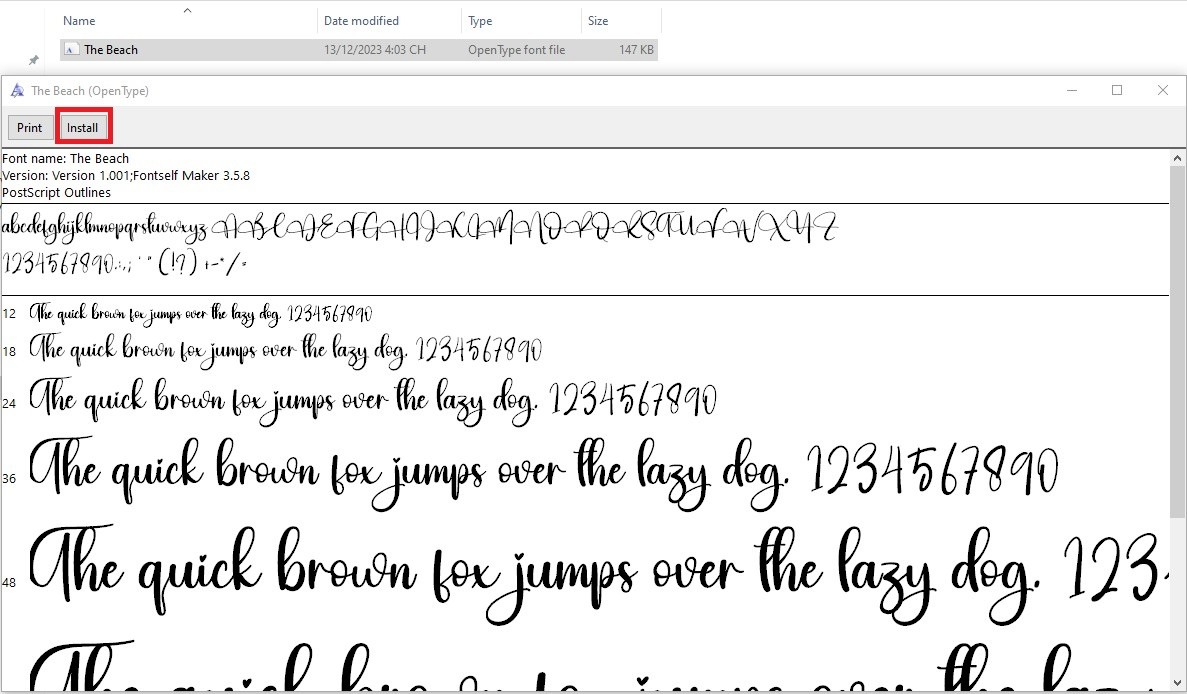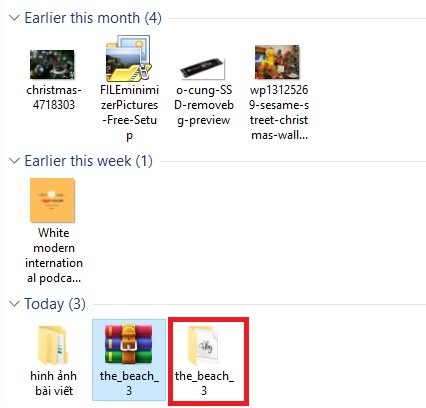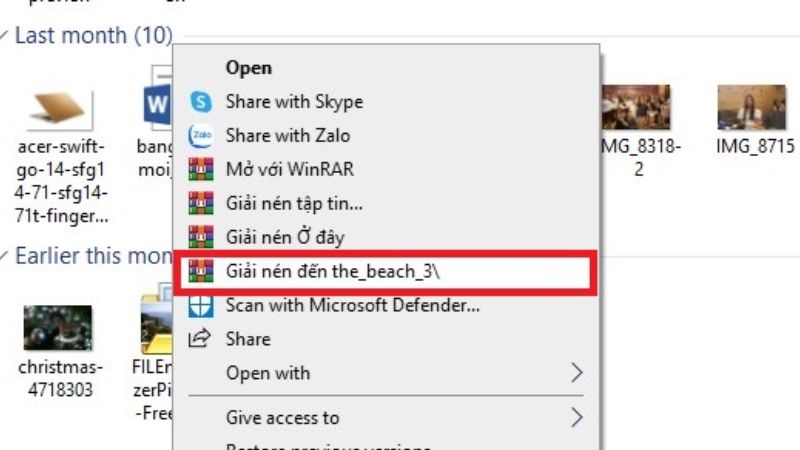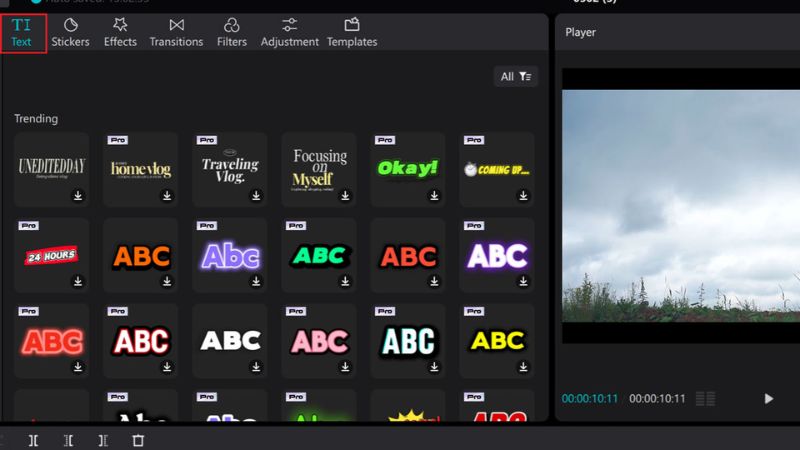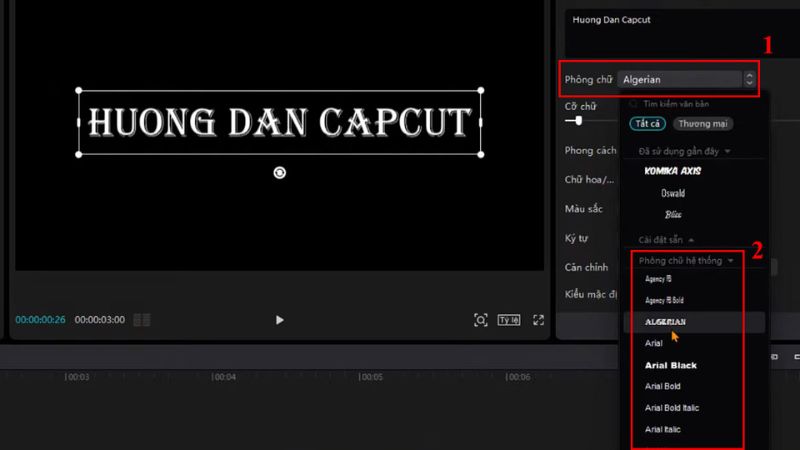
Thêm font chữ vào CapCut là một trong những giải pháp được nhiều người dùng lựa chọn khi muốn tạo ra những video chuyên nghiệp và mang đậm dấu ấn cá nhân,…. Tuy nhiên, không phải ai cũng biết cách thêm font chữ vào CapCut trên máy tính. Vì thế bài viết này của Điện Thoại Giá Kho sẽ hướng dẫn bạn cách thêm font chữ vào CapCut PC nhanh chóng và đơn giản nhất năm 2025.
Lợi ích khi thêm các font chữ vào CapCut PC
Việc thêm font chữ vào CapCut PC không chỉ đơn thuần là một bước tùy chỉnh giao diện văn bản, mà cách làm này còn mang lại nhiều lợi ích thiết thực cho những ai làm sáng tạo nội dung, đặc biệt là trong lĩnh vực video marketing, vlog, giáo dục hay giải trí. Dưới đây là những lợi ích nổi bật mà người dùng sẽ nhận được khi cài đặt font chữ tùy chọn vào CapCut PC:
Tăng tính thẩm mỹ cho video
Font chữ ảnh hưởng trực tiếp đến cảm nhận thị giác của người xem. Một font chữ phù hợp sẽ giúp phần tiêu đề nổi bật hơn, nội dung phụ dễ theo dõi hơn và tổng thể video trở nên chuyên nghiệp, cuốn hút hơn.
Đặc biệt, khi bạn kết hợp font chữ với hiệu ứng chuyển động, màu sắc và bố cục hợp lý, chất lượng video sẽ được nâng tầm rõ rệt, từ đó giúp video nổi bật hơn, thu hút người xem ngay từ cái nhìn đầu tiên.
Tư do sáng tạo, thể hiện dấu ấn riêng
Không bị giới hạn bởi những font mặc định nhàm chán, người dùng hoàn toàn có thể tạo nên chất riêng cho video của mình nhờ có kho font chữ đa dạng. Từ font hiện đại, đơn giản cho video công nghệ, đến font nghệ thuật, cổ điển cho những video tâm trạng, người dùng có thể thoải mái biến tấu theo ý tưởng và thông điệp muốn truyền tải.
Tạo sự chuyên nghiệp cho thương hiệu cá nhân, doanh nghiệp
Với những người làm branding hoặc kinh doanh online, việc sử dụng đúng bộ font theo nhận diện thương hiệu là yếu tố không thể thiếu. Khi thêm font chữ vào CapCut PC sẽ giúp người sử dụng đồng bộ phong cách thể hiện trên nhiều nền tảng, từ hình ảnh, website cho đến video, đem đến cảm giác nhất quán và chuyên nghiệp trong mắt khách hàng.
Hỗ trợ soạn nội dung tiếng Việt rõ ràng, không lỗi font
Nhiều font mặc định không hỗ trợ tiếng Việt hoặc hiển thị lỗi dấu, gây mất thiện cảm khi xem. Khi người dùng thêm các font Việt hóa vào CapCut PC, nội dung video sẽ được truyền tải trọn vẹn, dễ đọc, dễ hiểu hơn, nhất là đối với những video phụ đề, thuyết minh hay dạy học.
Như vậy, việc thêm các font chữ vào CapCut PC đem lại nhiều lợi ích cho người làm video. Nó không chỉ giúp nâng cao trải nghiệm người xem mà còn thể hiện sự chuyên nghiệp, tinh tế và sáng tạo trong từng khung hình.
Hướng dẫn chi tiết cách thêm font chữ vào CapCut PC nhanh, đơn giản
Để thêm font chữ vào CapCut trên máy tính, laptop bạn cần cần thao tác với các bước cơ bản sau:
Chuẩn bị font chữ trước khi thêm vào CapCut
Để bắt đầu, bạn cần lựa chọn những font chữ phù hợp với phong cách video mà bạn đang dựng. Cách đơn giản là tìm kiếm trên trình duyệt cụm từ như “font chữ đẹp cho CapCut”, sau đó truy cập vào các trang web uy tín để tải font về. Khi tìm thấy kiểu chữ ưng ý, chỉ cần nhấn vào nút “Tải xuống” hoặc “Download” là được.
Giải nén và cài đặt font vào máy tính
Sau khi tải về, các font thường nằm trong file nén định dạng .zip
. Bạn cần giải nén trước khi cài đặt:
Bước 1: Click chuột phải vào file nén, chọn “Giải nén tại đây” hoặc “Extract to…” tùy theo phần mềm giải nén bạn đang dùng.
Bước 2: Truy cập vào thư mục vừa được giải nén để tìm file font (thường có đuôi
Bước 3: Nhấn đúp chuột vào file font để mở nó lên.
Bước 4: Trong cửa sổ hiện ra, chọn “Install” để thêm font vào hệ thống máy tính.
Sử dụng font mới trong CapCut PC
Khi font đã được cài đặt thành công, hãy mở CapCut trên máy tính. Bạn có thể bắt đầu một dự án mới hoặc mở lại dự án đang làm. Để thêm chữ, chọn mục “Text” trong thanh công cụ. Tại đây, bạn nhập nội dung văn bản mong muốn.
- Trong phần lựa chọn font chữ, trong menu chỉnh sửa, bạn tìm mục “Phông chữ” và chọn font chữ vừa cài đặt.
Đâu là những lỗi thường gặp khi thêm font chữ vào CapCut PC?
Trong quá trình thêm font chữ vào CapCut PC, không ít người dùng gặp phải một số lỗi phổ biến ảnh hưởng tới quá trình chỉnh sửa video. Và sau đây là các lỗi hay gặp cùng cách khắc phục:
Font chữ không hiển thị trong công cụ CapCut
Font chữ không hiển thị trong phần mềm CapCut là lỗi thường gặp nhất. Nguyên nhân là do font chưa được cài đúng cách vào hệ điều hành hoặc CapCut chưa cập nhật danh sách font mới.
Để khắc phục lỗi này, người dùng cần đảm bảo đã cài đặt font đúng định dạng (.ttf hoặc .otf) và chọn lệnh “Cài đặt” hoặc “Install”. Sau đó, hãy khởi động lại CapCut để phần mềm nhận diện font mới.
Font bị lỗi ký tự, sai dấu tiếng Việt
Hiện có một số font không hỗ trợ Unicode tiếng Việt, như vậy sẽ dẫn đến tình trạng mất dấu, hiển thị ô vuông hoặc chữ bị biến dạng. Vì thế, khi thêm font chữ vào CapCut PC, người dùng nên ưu tiên sử dụng các font đã được Việt hóa hoặc hỗ trợ tốt như Roboto, Montserrat,…
Font chữ được thêm vào CapCut PC quá phức tạp, khó đọc
Việc chọn font chữ nghệ thuật quá cầu kỳ có thể khiến nội dung video mất đi tính chuyên nghiệp. Vì thế, người dung nên chọn những font rõ ràng, dễ nhìn, nhất khi sử dụng để tạo video hướng dẫn, review sản phẩm hoặc quảng cáo.
Vi phạm bản quyền khi thêm font chữ
Việc sử dụng font chữ không rõ nguồn gốc có thể dẫn đến rắc rối pháp lý do vi phạm bản quyền, nhất là khi sử dụng làm video thương mại. Vì vậy mà người dùng hãy dùng các font miễn phí có bản quyền từ Google Fonts hoặc các nguồn uy tín khác.
Thêm font chữ vào CapCut PC cần lưu ý gì?
Khi thêm các font chữ vào CapCut PC, bạn cần lưu ý một vài điểm quan trọng dưới đây:
- Hãy chắc chắn rằng font bạn chọn hỗ trợ tiếng Việt đầy đủ. Nhiều font đẹp trên mạng chỉ hiển thị tốt tiếng Anh, còn tiếng Việt lại bị lỗi dấu hoặc biến thành ô vuông. Như vậy, điều này có thể làm hỏng cả bố cục và cảm xúc trong video.
- Nên ưu tiên những font miễn phí cho mục đích thương mại, nhất là nếu bạn muốn làm video để đăng YouTube, quảng cáo hay cho khách hàng.
- Ngoài ra, bạn chỉ nên cài những font thực sự cần thiết. Cài quá nhiều font không chỉ khiến CapCut load chậm mà còn làm máy tính hoạt động ì ạch.
- Sau khi cài font mới, hãy khởi động lại CapCut để phần mềm nhận diện được. Và trước khi xuất video, nhớ xem lại để đảm bảo font hiển thị đúng như bạn mong muốn. Một vài phút kiểm tra kỹ lưỡng sẽ giúp bạn tránh được những lỗi đáng tiếc sau này.
Tóm lại, việc thêm font chữ vào CapCut PC không chỉ giúp video của bạn trở nên sinh động và chuyên nghiệp hơn mà còn thể hiện được phong cách cá nhân của bạn. Chỉ với vài bước đơn giản, bạn đã có thể mở rộng kho font chữ của mình và tạo ra những video ấn tượng. Hãy áp dụng và khám phá sự khác biệt mà font chữ mang lại cho video của bạn ngay hôm nay!